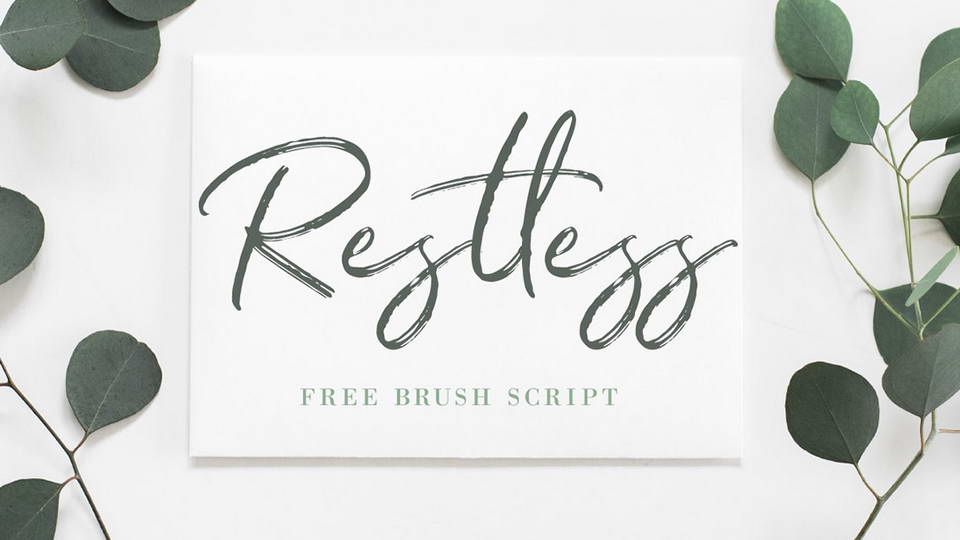
Любая субкультура имеет свои отличительные признаки: панки и металлисты предпочитают слушать тяжелую музыку, хиппи демонстрируют приверженность идее свободы и всеобщей любви, ролевиков объединяют важные исторические события. Помимо культурной составляющей, представители любого неформального течения выделяются и манерой одеваться. Даже не особо разбирающийся в этом вопросе человек сразу отличит панка от эмо или байкера от хипстера. Уж очень они разные, несмотря на то, что все до единого являются нонкомформистами. Есть и другие атрибуты той или иной субкультуры. Например, шрифты.
Есть свои, причем очень характерные, шрифты и у хипстеров. Их любовь к винтажным вещам нашла свое отражение не только в одежде, но и в типографике. Хипстерские шрифты зачастую напоминают рукописные, они немного старомодные и вполне «мирные», несмотря на часто встречающуюся псевдобрутальность. На сегодняшний день хипстеры являются одним из самых массовых молодежных течений и дизайнерам важно знать, какие тренды являются самыми актуальными в этой очень самобытной субкультуре. FreelanceToday предлагает вашему вниманию 10 бесплатных «хипстерских» шрифтов.
HOMESTEAD
Шрифт Homestead по праву считается одним из самых популярных хипстерских шрифтов. Шрифт не новый, дизайнер Люк Лиси впервые представил его в 2011 году. Homested это яркий представитель брусковых шрифтов с крупными засечками, он очень массивный и выглядит внушительно. При этом он вовсе не агрессивный, несмотря на легкий налет брутальности. Шрифт отлично подойдет для набора заголовков, он отлично сочетается с самыми разными хипстерскими принтами.
HIGHLAND
Создатель шрифта Highland – дизайнер и предприниматель Тайлер Галпин. Это один из первых шрифтов, созданных им для своей компании Lost Type Co-Op. Highland получился на редкость удачным, это стильный и в меру брутальный брусковый шрифт с засечками. В отличие от Homestead, он выглядит более легким, чувствуется, что дизайнер искал вдохновение в ретро-плакатах. Шрифт универсальный, очень доброжелательный, он отлично подойдет для набора больших заголовков. Несмотря на толстые вертикальные и горизонтальные штрихи, шрифт выглядит вполне неформально, а значит, «по-хипстерски».
DUMA
Шрифт Duma похож на шрифты, популярные в 70-х годах ХХ века. Это очень сбалансированный шрифт без засечек, который отличается тонкими длинными вертикальными штрихами и такими же перемычками.
AIRBAG
Создатель шрифта Airbag – дизайнер Саймон Стратфорд. Данный шрифт является его дебютом, но дебютом вполне удачным. Дизайнеру каким-то образом удалось ухватить хипстерский дух, шрифт получился очень запоминающимся. Может быть, причина заключается в его псевдообъемности – Airbag относится к группе шрифтов с затенением, которые были очень популярны на протяжении нескольких десятилетий прошлого века.
Шрифт неформальный, но при этом строгий, с тонкими основными штрихами и маленькими аккуратными засечками. В бесплатной версии Airbag доступны только глифы верхнего регистра. Чтобы получить доступ к строчным буквам и другим символам, придется потратить $15. Создатель шрифта предупреждает, что бесплатную версию Airbag можно использовать в интернете только с его предварительного согласия.
CHASE
Chase это очень сильно вытянутый по вертикали шрифт без засечек. Он не винтажный и не футуристичный, это именно современный шрифт, отражающий большинство актуальных трендов. Основные штрихи длинные и тонкие, а горизонтальные перемычки сильно занижены, что придает символам неповторимую индивидуальность. Шрифт легкий, стильный, немного холодный. В нем нет агрессии или напора – Chase яркий представитель нейтральных хипстерских шрифтов. Несмотря на тонкие штрихи и малую ширину символов, шрифт очень разборчивый, поэтому им можно набирать как заголовки, так и небольшие текстовые блоки.
AQUA
При создании шрифта Aqua графический дизайнер Лора Пол вдохновлялась эстетикой 40-х годов прошлого века. Aqua – не совсем типичный гротеск, это красивый и элегантный шрифт, который выглядит вполне современно, несмотря на легкие отсылки к винтажу. Шрифт включает в себя символы верхнего и нижнего регистра, а также цифры и дополнительные символы. Выглядит Aqua вполне по-хипстерски, в меру строго и стильно. Шрифт бесплатный, его можно использовать как в личных, так и коммерческих проектах. Лучше всего Aqua подойдет для набора заголовков, его можно использовать при создании плакатов, листовок и другой печатной продукции. В цифровой среде Aqua также смотрится очень достойно, несмотря на несколько увеличенное расстояние между символами. Строчные буквы достаточно разборчивы для того, чтобы было можно набирать данным шрифтом небольшие фрагменты текста.
A Day Without Sun это очень интересная версия шрифта Panforte, созданная дизайнером Козимо Лоренцо Панчини. Как и его предшественник, данный шрифт относится к группе рукописных, но, в отличие от Panforte, он сильно заужен. Его длинные тонкие штрихи позволяют использовать шрифт в случае, если нужно, к примеру, имитировать стиль старинных ресторанных меню, которые заполнялись от руки. Те, кому нравятся стильные рукописные шрифты, обязательно оценят этот набор — A Day Without Sun поддерживает свыше сорока языков, в том числе и кириллицу, что встречается редко в сегменте неформальных шрифтов. Несмотря на то, что шрифт очень узкий, он достаточно разборчив. Однако им не следует набирать более двух-трех строчек кряду, иначе текст станет нечитаемым. A Day Without Sun прекрасно подойдет для оформления открыток и приглашений, его можно использовать в дизайне упаковки, но лучше всего он смотрится в цифровой среде.
STEELWORKS
Создатель шрифта Steelworks дизайнер Эрик Бернтиллдед стремился к имитации штрихов, которые оставляет полусухая плоская кисть.
В этом случае штрихи получаются немного неряшливыми, но зато сами буквы выглядят очень естественно. То есть, вполне по-хипстерски. Данный шрифт можно использовать практически где угодно, это мягкий гуманистический сан-сериф, который можно отнести к группе акцидентных шрифтов. Большие массивы текста набирать шрифтом Steelworks не рекомендуется, а вот для заголовков он подходит как нельзя лучше. Шрифт одновременно винтажный и современный, очень дружелюбный, а симпатичные завитушки символов R и S делают его в меру игривым.